Tổng hợp các mẫu font chữ Vintage xu hướng hiện nay được nhiều người dùng nhất
Font chữ Vintage hiện nay đang là xu hướng được rất nhiều người thể hiện trong thiết kế của mình vì nó mang đậm nét cổ điển và sự trường tồn với thời gian. Để chiêm ngưỡng vẻ đẹp của font chữ Vintage, trong bài viết này FPT shop sẽ giúp các bạn cảm nhận được vẻ đẹp cổ điển qua từng mẫu font chữ Vintage cụ thể.
1. Font chữ Vintage là gì?
Vintage theo nghĩa Tiếng Anh có nghĩa cổ điển, cũ và được sử dụng hầu hết trong rất nhiều lĩnh vực đặc biệt là: thời trang, nội thất và đồ họa. Với nghĩa đó, phong cách Vintage là phong cách của kỉ niệm, khơi gợi những vẻ đẹp của quá khứ, của thời gian. Có thể nói, Vintage là một từ chứa đựng ý nghĩa sâu sắc về vẻ đẹp, phong cách cũng như thời gian.
Trong thiết kế đồ họa, font chữ là một yếu tố quan trọng và quyết định được phong cách đặc biệt cho thiết kế của mình. Do đó, việc chọn lựa thiết kế theo font chữ phong cách nào là một vấn đề cần chú trọng. Font chữ Vintage là kiểu chữ mang phong cách cổ điển nhưng lại rất sang trọng, thu hút người nhìn.
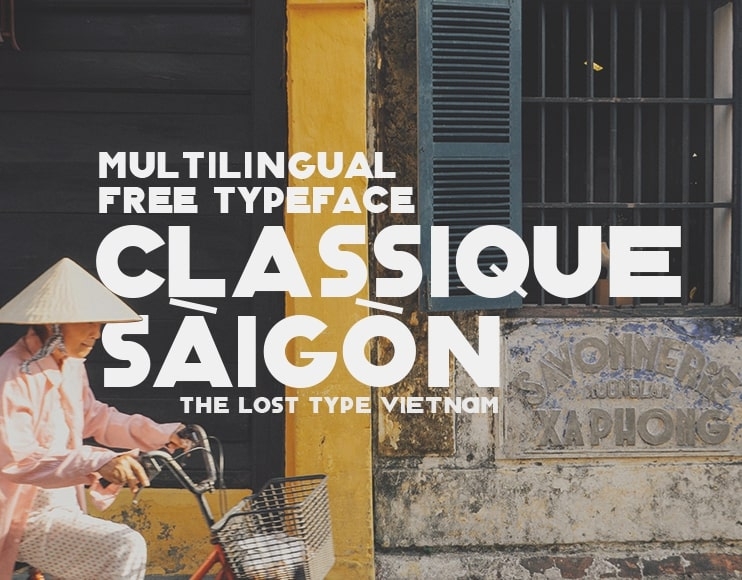
Font chữ Vintage hiện nay vẫn chứng tỏ được tầm quan trọng của mình vì nó chưa bao giờ lỗi thời so với cái ý nghĩa cổ điển của nó. Việc kết hợp phong cách Vintage trong thiết kế tạo nên cho bạn một tác phẩm thật hoàn hảo, sang trọng mà vẫn giữ được nét đẹp cổ điển mà vẫn hiện đại.
2. Một số font chữ vintage hot nhất hiện nay
2.1. Font chữ Vintage bóng đèn Neon
Font chữ Vintage bóng đèn Neon là kiểu chữ có khả năng phát sáng làm nổi bật những tấm biển hiệu hoặc quảng cáo. Sự phát sáng này do đèn Neon phát ra khi khí Neon có dòng điện chạy qua. Font chữ Vintage Neon được sử dụng chủ yếu trong một số thiết kế như banner quảng cáo, logo, nhãn hiệu, văn phòng phẩm, thiệp cưới,…
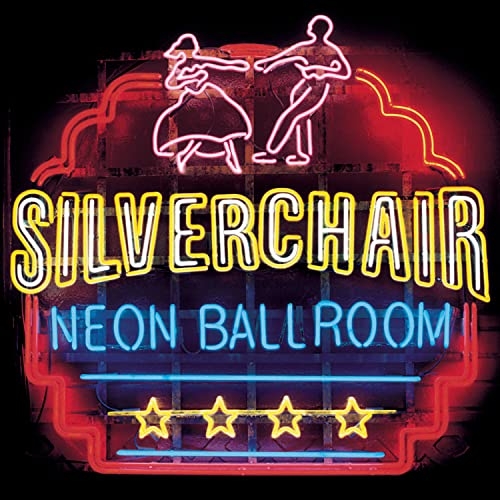
2.2. Font chữ Vintage hoài cổ
Font chữ Vintage hoài cổ xứng đáng là lựa chọn tuyệt vời cho những thiết kế mang phong cách xưa, đặc biệt là những nội dung truyền thông hướng đến văn hóa, lịch sử Việt nam những năm thời kháng chiến.
2.3. Font chữ Vintage lai hiện đại
Font chữ Vintage lai hiện đại là sự kết hợp tuyệt vời giữa vẻ đẹp cổ điển pha chút hiện đại. Chính sự kết hợp hoàn hảo này đã đem đến một phong cách mới mẻ và tạo điểm nhấn cho thiết kế của bạn.
2.4. Font chữ Vintage sang trọng
Đối với những ai yêu thích phong cách cổ điển mà vẫn muốn sang trọng trong thiết kế thiệp cưới thì font chữ Vintage là một lựa chọn vô cùng chính xác. Nhìn vào cách thiết kế vintage của thiệp cưới đã toát lên một đám cưới rất sang trọng của cô dâu và chú dể.
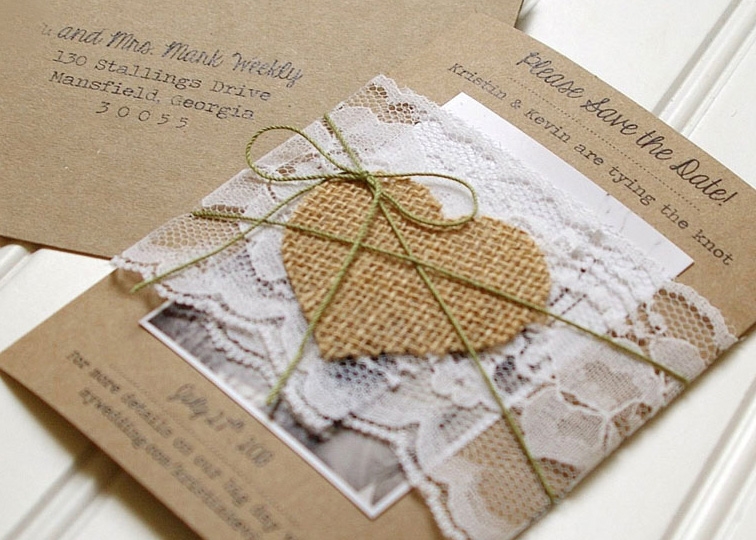
2.5. Font chữ Vintage phai mờ
Font chữ Vintage phai mờ cũng là một phong cách đem lại dấu ấn thời gian và có ý nghĩa vô cùng sâu sắc về sự bền bỉ với năm tháng. Cho dù có sự phai mờ về vết mực nhưng dấu ấn của nó trong lòng mỗi người là vẫn còn nguyên vẹn và trường tồn cùng với thời gian.
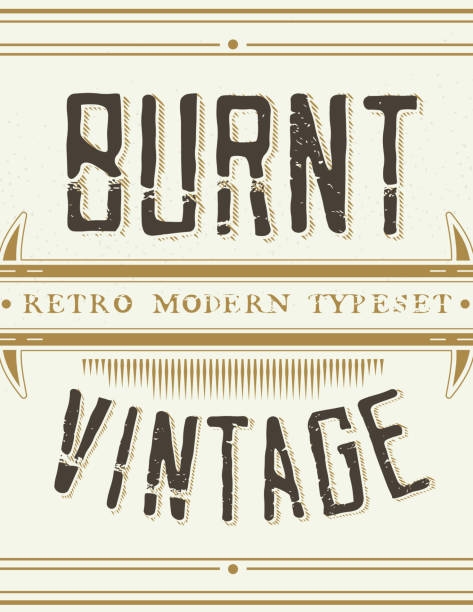
2.6. Font chữ Vintage viết sách
Để tạo nên điểm nhấn cho cuốn sách mới xuất bản, các nhà thiết kế rất trú tâm trình bày và chọn font chữ nào để khi xuất hành ấn phẩm sẽ gây ấn tượng tới người đọc. Font chữ Vintage vẫn là lựa chọn hàng đầu được thể hiện trong nhiều ấn phẩm bởi nét đẹp cổ điển và hiện đại của nó là một vẻ đẹp không thể phủ nhận được.
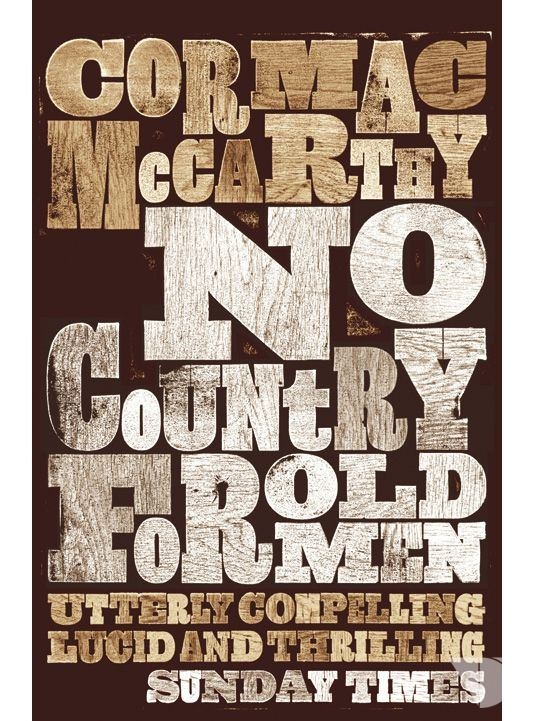
Trên đây là một vài font chữ Vintage thường được các nhà thiết kế sử dụng nhất. Còn rất nhiều mẫu font chữ Vintage khác các bạn có thể dễ dàng tìm kiếm trên mạng để tham khảo và sử dụng.
Lời kết
Xu hướng sử dụng font chữ Vintage hiện nay ngày càng phổ biến trong nhiều ấn phẩm và thiết kế. việc tham khảo và lựa chọn kiểu mẫu nào phù hợp và đem lại hiệu quả cho thiết kế của mình cũng là một yếu tố rất quan trọng. Do đó, các bạn hãy dựa vào ý nghĩa và mục đích của thiết kế của mình để chọn lựa font chữ Vintage phù hợp nhất.